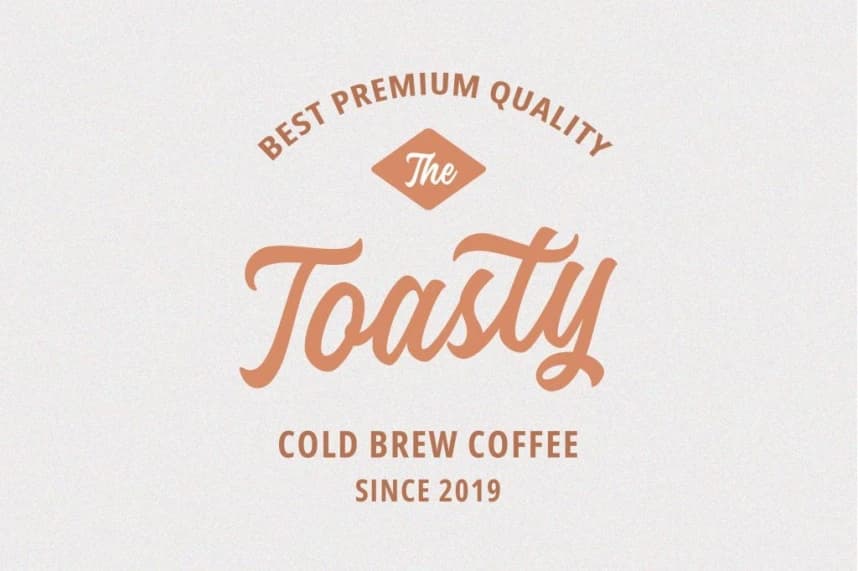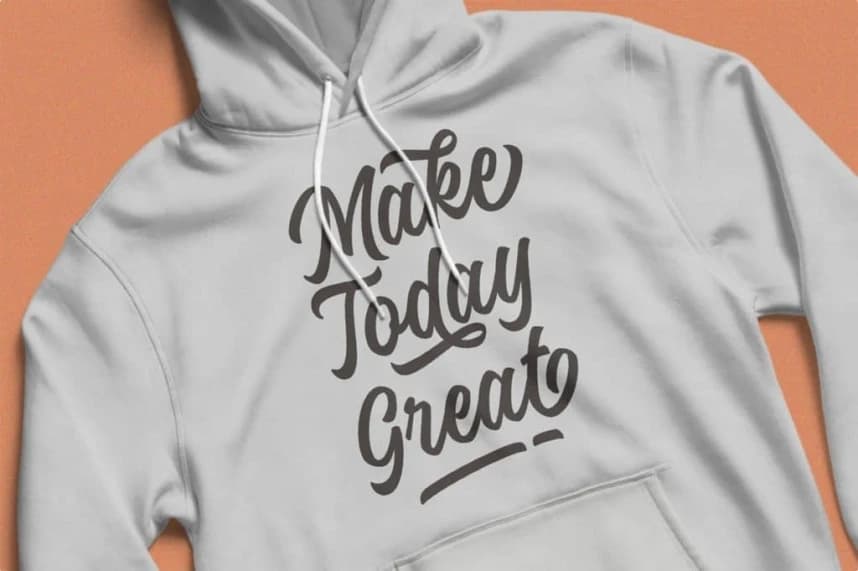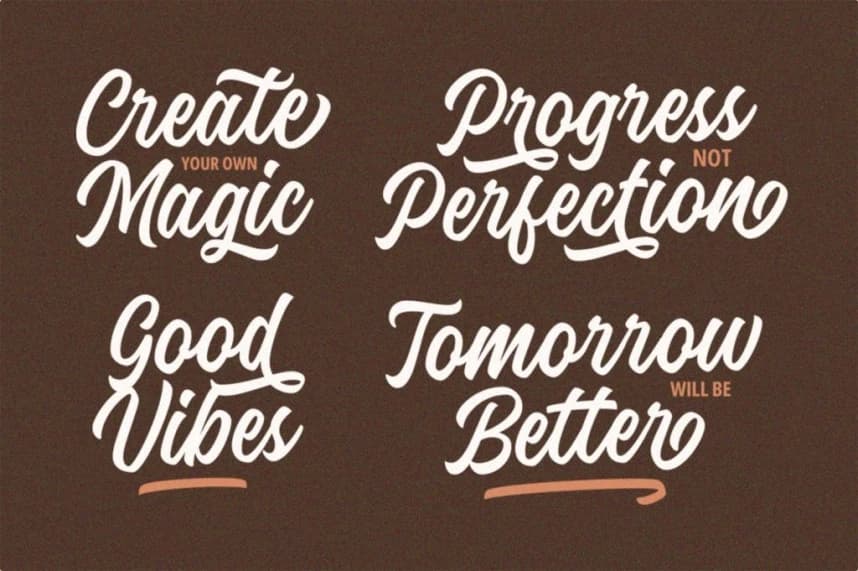
Candale Script Font
Candale Script Font - doğal vintage görünümlü fırça yazı tipi. Logotip tasarımı için, kıyafet tasarımı için, alıntılar için, düğün tasarımları için, sosyal medya gönderileri için, ürün ambalajı için, etiketler için, fotoğrafçılık için, afişler için ve diğerleri için kullanabilirsiniz.
Candale Script Font - doğal vintage görünümlü fırça yazı stili. Logotip tasarımı, giysi tasarımı, alıntılar, düğün tasarımları, sosyal medya gönderileri, ürün ambalajı, etiketler, fotoğrafçılık, afişler ve diğerleri yapmak için kullanabilirsiniz.
Candale Script